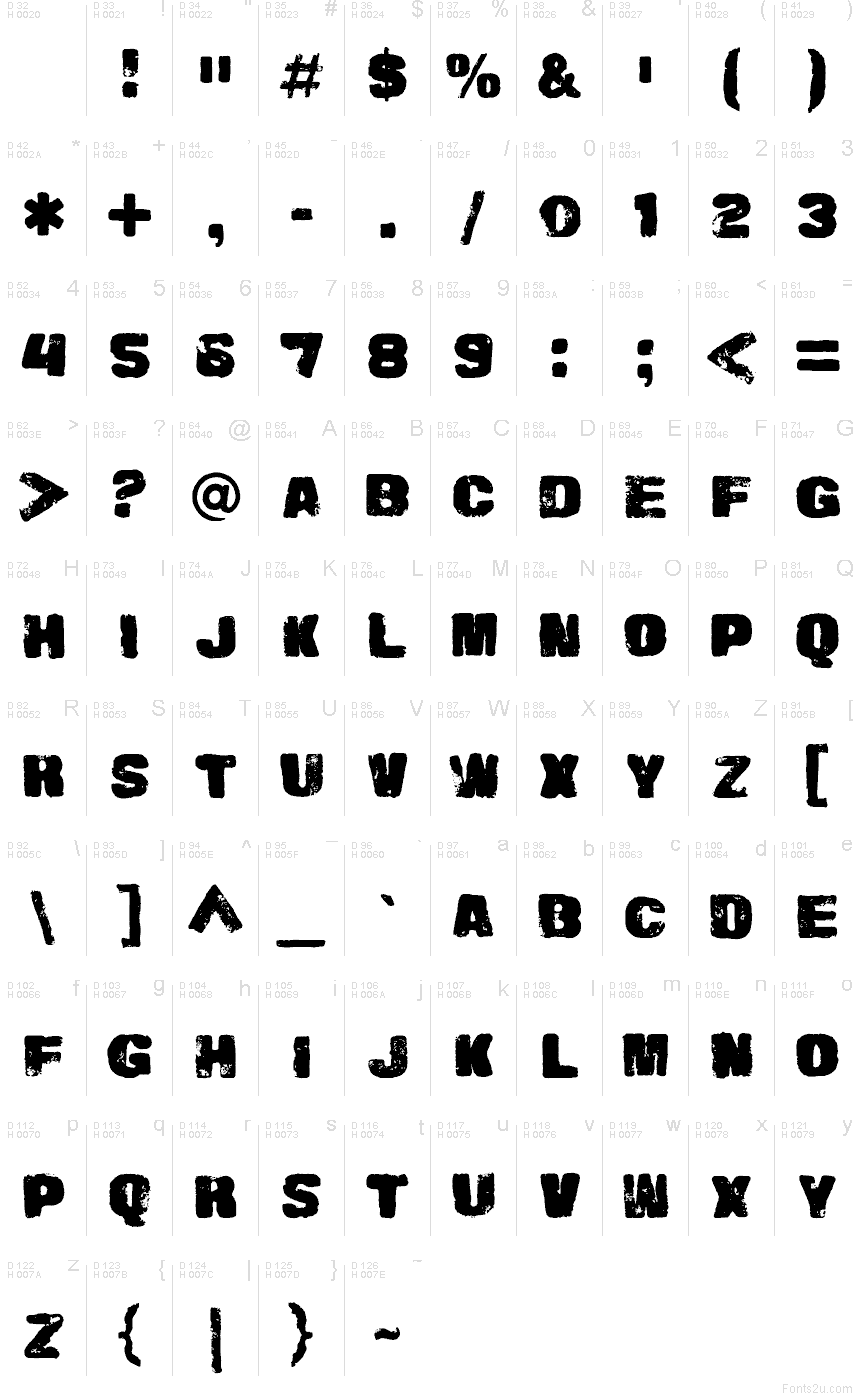
Snailmate Regular
La police Snailmate, créée par Tension Type, est une fonte d'affichage gratuite à l'aspect érodé, avec des bords irréguliers et des découpes qui morcellent chaque lettre. Si les formes paraissent robustes au premier coup d'œil, leur texture endommagée confère à l'ensemble un caractère marqué par l'usure et le temps.
Snailmate est idéale pour les pochettes d'albums, les titres d'affiches, les packagings d'horreur, l'art du jeu vidéo ou la mode underground : sa surface abîmée apporte immédiatement une esthétique brute et usée à vos créations. Cette police gratuite est également parfaite pour les fanzines, les flyers événementiels et les logos audacieux lorsqu'un design nécessite un lettrage qui semble plus battu que poli.
Snailmate est née d'un jeu de lettres en mousse trouvé dans une friperie. Il manquait quelques caractères et le lot ne contenait que des majuscules sans aucune ponctuation. J'ai peint les lettres, les ai scannées, puis j'ai créé les caractères manquants en m'inspirant de ceux dont je disposais.
Snailmate started with a foam set of letters I found in a thrift store. It was missing a couple of characters and had only uppercase and no punctuation. I used paint to make the letters and scanned them. I created the rest based on what I had. Hopefully it’s just what you needed.